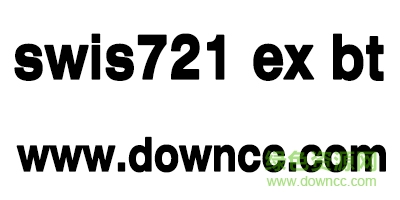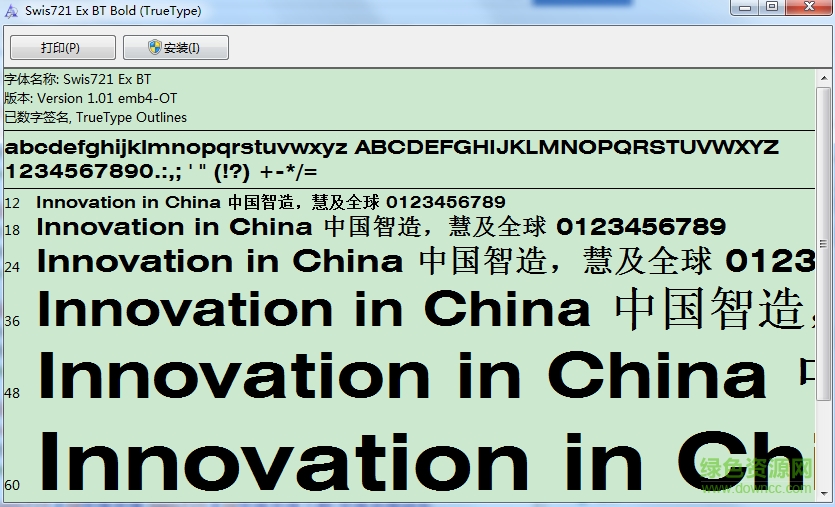
swis721 ex bt是一款一款粗重厚實的英文字體,視覺效果矚目,極具立體感,適合用于排版印刷、標(biāo)題制作等方面,有強調(diào)的效果。需要的朋友快來綠色資源網(wǎng)下載吧!
swis721 ex bt字體是一款深受用戶喜愛的英文字體,此款字體易讀性非常強,字體相對來說比較完整,應(yīng)用范圍比較廣泛,喜歡的朋友歡迎來綠色資源網(wǎng)下載收藏!